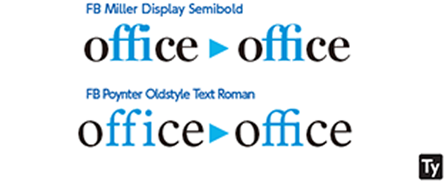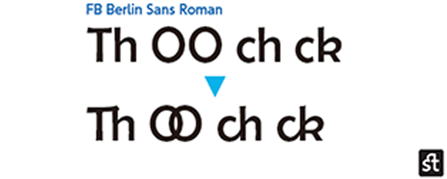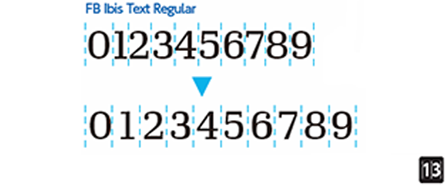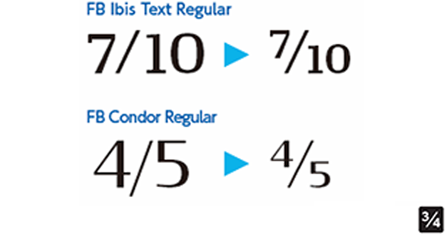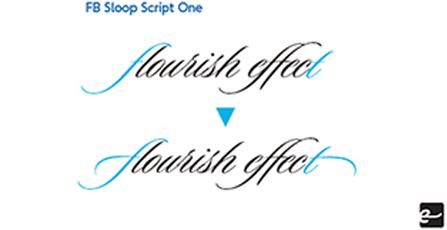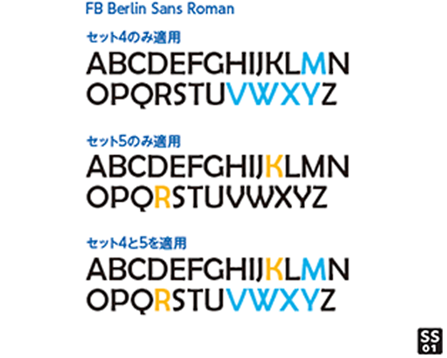
モリサワが提供するラテン文字(欧文フォント)に含まれる主なOpenTypeフォント機能についてご紹介します。
※搭載されているOpenType機能を画像右下のアイコンで表しています。
欧文合字/Standard Ligatures
「f」と「i」や「f」と「l」などが隣りあった場合、2つが重なって黒い塊になったり、文字間が不揃いに見えることがあります。「欧文合字」を適用すると、あらかじめ合字(リガチャ)としてデザインしたグリフや、字間が調節されたグリフに置き換わります。デフォルトで適用されています。
任意の合字/Discretionary Ligatures
フォントによっては欧文合字のほかに、より多くの合字を含んでいるものがあります。たとえば「FB Berlin Sans」ではThをはじめOO、ch、ckなど特殊な組合せの合字が含まれています。
スモールキャップス/Small Capitals
スモールキャップスは、大文字をおよそ小文字の高さに揃えてデザインしたグリフです。適用すると小文字がスモールキャップスに置き換わります。
すべてスモールキャップス/Small Capitals From Capitals
大文字と小文字の両方をスモールキャップスに置き換えたい場合に適用します。
オールドスタイル数字/Oldstyle Figures
本文組の中でライニング数字を使用すると、高さが違うため目立ってしまう場合があります。小文字とほぼ高さが揃ったオールドスタイル数字を適用することで、本文になじませることができます。
等幅ライニング数字/Tabular Figures
「デフォルトの数字」がそれぞれのキャラクタにふさわしい字幅をもったプロポーショナル数字になっている場合、表組みなどで桁を揃えたい場合には、等幅ライニング数字を適用します。
スラッシュを用いた分数/Fractions
数字とスラッシュを連続させて入力し適用させると分数に組換えます。1/2、1/4、3/4のみ対応するフォントと、分子、分母グリフを0から9まで揃え、桁数が多い分数の組版も可能なフォントがあります。
上付き序数表記/Ordinals
スペイン語やイタリア語で、序数表記として数字に連続して「a」 や「o」( 小文字のオー)を上付き序数表記として表示させたい場合に適用します。
スラッシュ付きゼロ/Slashed Zero
数字の「0 」(ゼロ)とアルファベットの「O 」(大文字のオー)を 識別するために、ゼロにスラッシュが付いたグリフが搭載されています。
スワッシュ字形/Swash
「FB Berlin Sans」には大文字の「Q 」にスワッシュ字形がバリエーションとして含まれています。適用させると長いテールをもったデザインに置き換わります。
デザインのバリエーション/Stylistic Alternatives
「FB Ibis Text」や「FB Berlin Sans」には標準のグリフとは 別のデザインバリエーションが含まれています。 ※InDesignでは「字形パネル」から利用します。「文字パネル> OpenType機能」から適用させることはできません。
位置依存形/Initial Forms, Terminal Forms
「FB Sloop」はカリグラフィらしい華やかな飾りがついたデザインですが、位置依存形の「語頭形」を適用させると小文字「f」と「t」が先頭用の、「語尾形」を適用させると「f」と「p」が末尾用のフローリッシュ(飾り)が追加されたグリフに置き換わります。「自動形」を適用させておくとこれらのグリフが単語の先頭、末尾に組まれた場合に自動的に置き換えられます。
デザインのセット/Stylistic Set
デザインのバリエーションを「デザインのセット」として組込んでい るフォントもあります。「デザインのバリエーション」と重複するデ ザインもありますが、さらに細分化し、傾向の似通ったデザインがセットとして登録されていますので、必要なものだけを適用させることが可能です。